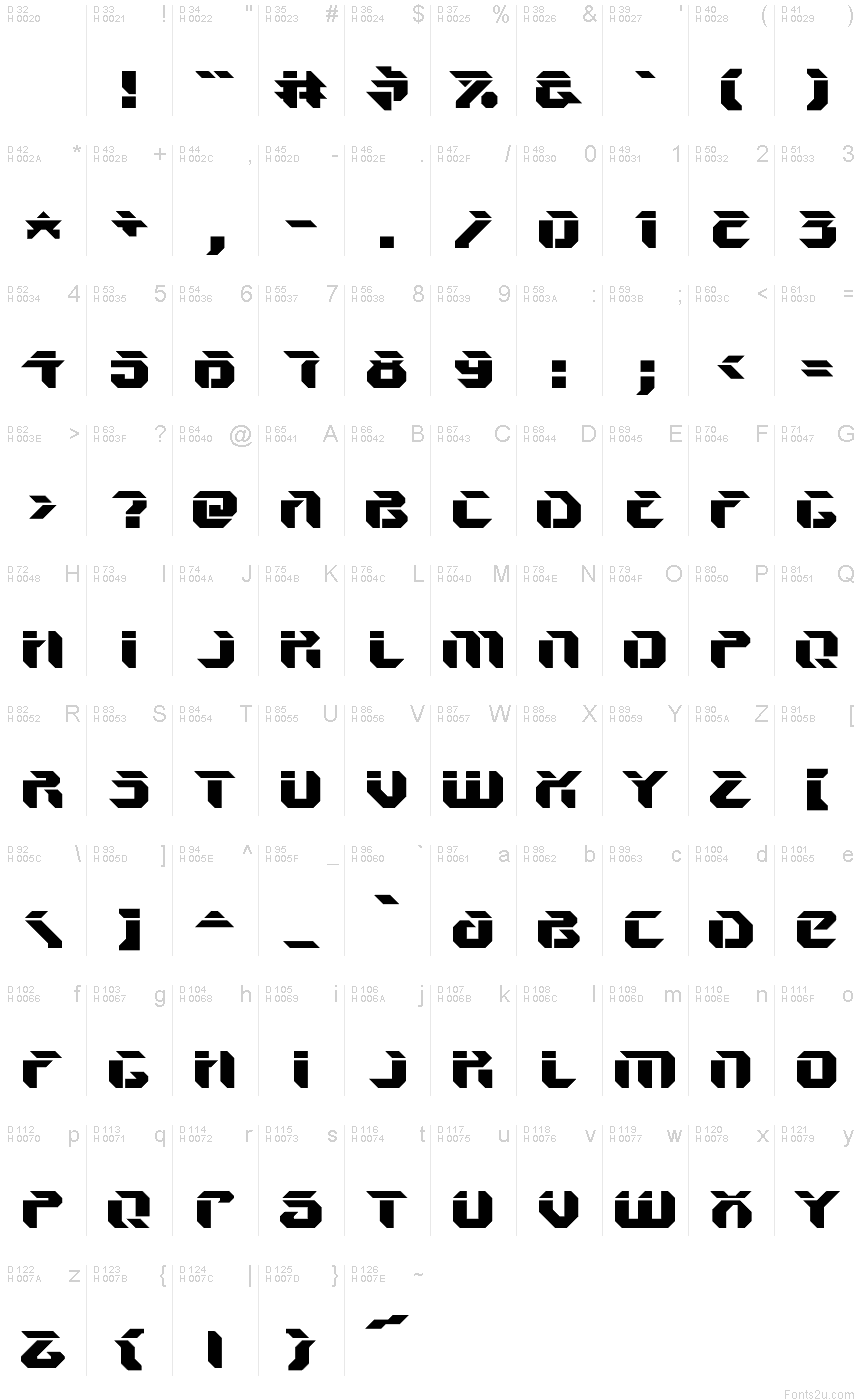
V5 Ampon Upright, il font techno display gratuito di Roberto Christen, punta su un look digitale tagliente, con maiuscole massicce dai tratti diagonali affilati e angoli quadrati. Le lettere appaiono compatte e progettate, con tacche profonde e angoli smussati che rendono questo carattere più simile a una segnaletica meccanizzata che a un normale font geometrico.
È perfetto per i titoli che richiedono un'estetica sintetica e decisa: loghi di videogiochi, flyer per club, poster, branding per eventi tech e nomi su packaging si prestano benissimo a questo font gratuito. Usalo per brevi righe, titoli o monogrammi, dove quei tagli angolari densi e il ritmo verticale lasciano subito il segno.